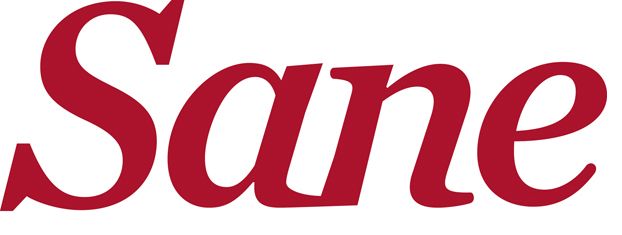
Foro de Tipografía ¿Existe esta tipografía? el 29.04.2015 a las 18:00 por raularte · 1 comentario Seguir este tema Dejar de seguir este tema 2 seguidores Hola Tengo dudas de que esto sea una tipo real, más bien me parece una transformación de alguna Century o algo así. ¿Alguien puede ayudarme? Muchas gracias Comentar Me gusta
Creo que que se trata de la Chronicle Text cursiva de Hoefler+Frere-Jones: